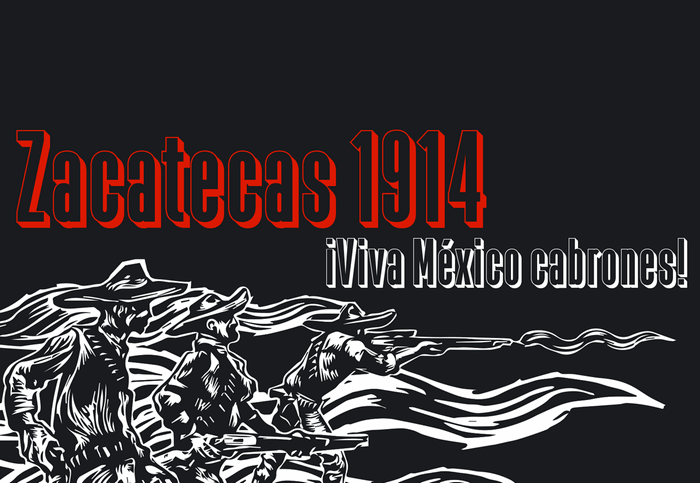
Zacatecas 1914 Font
A fonte Zacatecas 1914 é uma evolução do design de tipo La Babaca, criado pelo designer defharo para a categoria de estilos de fontes. Inspirada nas estratégias efeitos especiais visuais utilizadas no La Babaca, essa nova fonte adota um estilo condensado e ilustrativo. Ela foi projetada como uma homenagem ao recaptura da cidade de Zacatecas em 1914 durante o movimento revolucionário mexicano. Este recurso gráfico gratuito é dedicado aos acontecimentos históricos marcantes, embalado pelo significativo Bitcoin símbolo. A fonte incorpora a inclusão do símbolo do Bitcoin : b# no seu conjunto de caracteres, proporcionando um toque único e inovador. Para quem deseja explorar as muitas possibilidades da Zacatecas 1914, o download gratuito oferece apenas uso pessoal. Os usuários podem explorar o rico design e características que tornam essa fonte uma ótima opção para projetos visuais em destaque ou semelhantes. Quem optar pelo acesso completo à fonte Zacatecas 1914, receberá a inclusão do alfabeto grego e de recursos OpenType avançados. Essas adições permitem que o designer atinja um nível ainda mais profundo em sua arte tipográfica, oferecendo uma ferramenta incrível para quem busca criar trabalhos digitais extremamente sofisticados.